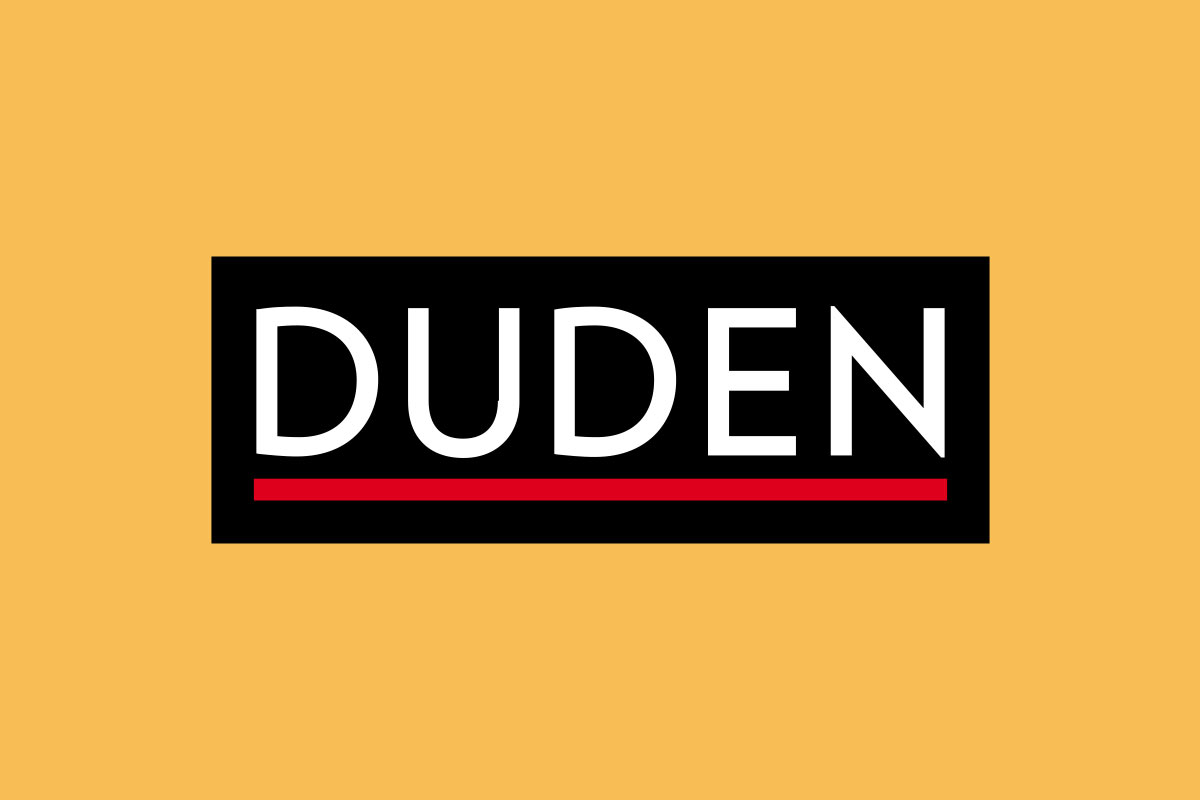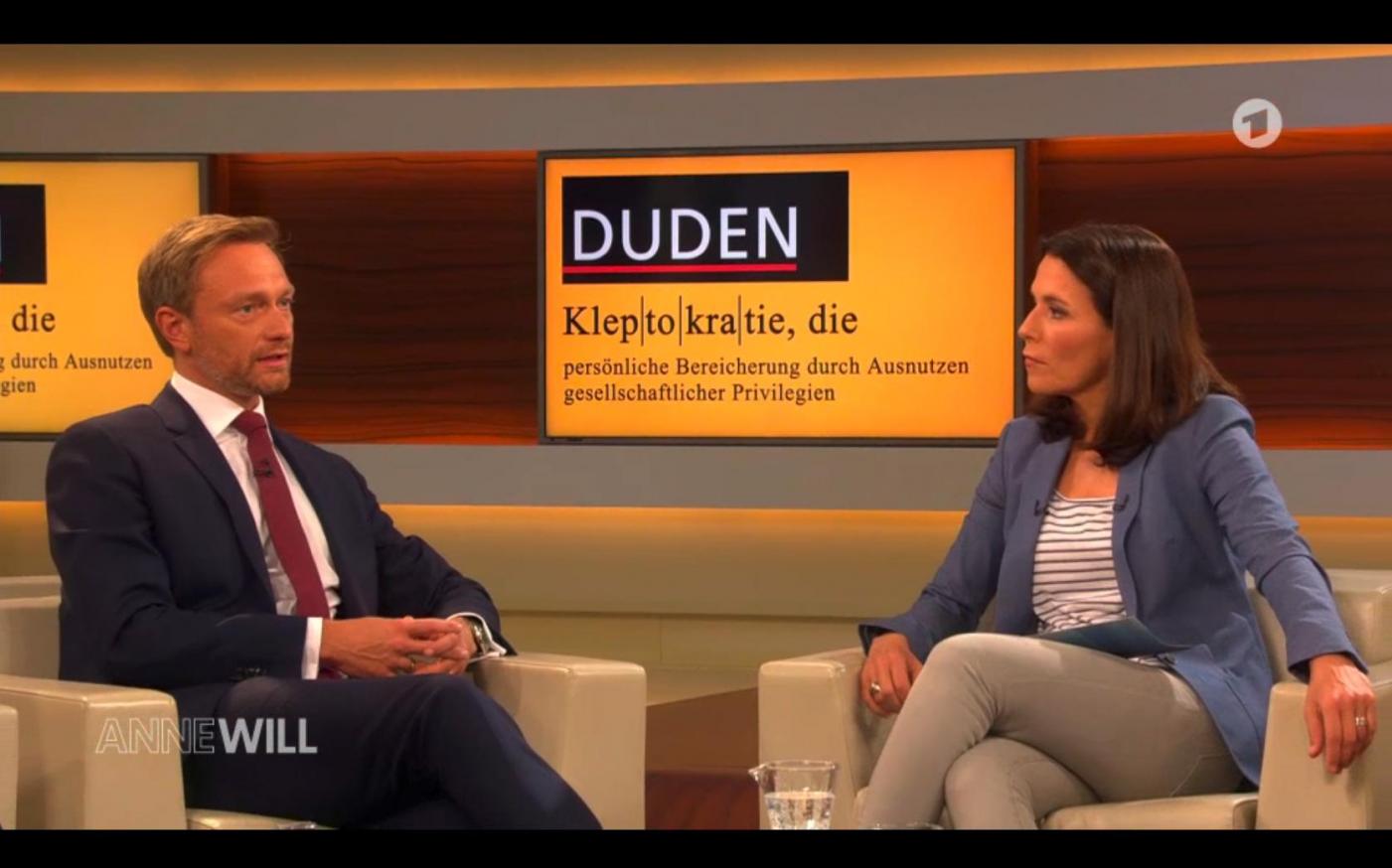
Neues Duden-Design
Vermutlich sollte es »anders, frischer und moderner« aussehen*.
Das aber unter unbedingter Beibehaltung aller signifikanten Gestaltungsmerkmale.
Wasch mich, aber mach mich nicht nass.
Gestalte mich, aber mach mich nicht schön.
*Nachtrag: Das ist die große alte Dame unter den schlechten Briefings.
"Angeschnitten" ist doch schon ein paar Jahre wieder vorbei. Unnötiges Aufbrechen der Ordnung – lässt bei mir Zweifel an der Ernsthaftigkeit aufkommen. Schade. Die sattere Farbe ist ja ein guter Schritt, ich hätte aber eher ein Gelb (so kennen wir den Duden) als ein Orange genommen.
Ich finde, dass es nicht grundsätzlich schlecht ist, Text an- bzw. abzuschneiden. Nur in Bezug auf die neue Ausgabe des Dudens sieht der angeschnittene Schriftzug nach Lückenfüller aus. Einer der beiden Schriftzüge „DUDEN” verkommt zum rein grafischen Element. Der Umgang mit den Leerräumen ist also bei der neunten Auflage besser. In Bezug auf die Funktionalität hätte einer völlig ausgereicht. Darüber hinaus ist der helle Text auf dem Orange nicht gerade gut lesbar.
Aber auch das Design des Covers der neunten Auflage ist nicht wirklich gut. Die versetzte unterstreichende Linie reicht bis zum linken Rand. Vermutlich weil der Text recht nahe am linken Rand der schwarzen Fläche liegt. Die Linie sieht so zwar „definierter” aus, aber im Grunde ist sie ohnehin überflüssig.
Na ja, so richtig mach ich dieses Schriften-Durcheinander da auch nicht. Mindestens 3 verschiedene, und DUDEN in 2 Verschiedenen Schriften?
Frohes Fest – da könnte ich jetzt länger drüber schreiben (und geht dann schon mal gut los), weil ich an dem »Relaunch« des Duden im Jahre 2000 maßgeblich als Freelancer beteiligt war (siehe „Vorher“). Die Reinzeichnung der Logotype (meist angeschnittenes schwarzes Fähnchen, wurde dann aber auch alleinstehend als Logo eingesetzt), stammt von mir, basierte auf einer minimal modifizierten Frutiger Roman.  Vorher gab es kein »Duden-Logo«, es gab zwar eine grafische Linie in der Einbandgestaltung, die auf einer durch Günter Gerhard Lange überarbeiteten Times basierte. Der Gedanke, den Markennamen Duden in eine grafisch konsistente Form zu bringen, sprich also eine Logotype zu gestalten, die als Element der Einbandgestaltung, wie auch alleinstehend Verwendung finden konnte, war damals neu.
Dennoch gab es einige Konstanten, wie z.B. den „Regenbogen“ für die Kernbände, die beibehalten wurden – die Pixel kamen später dazu. Der Spektralverlauf ist eine Erbschaft von Willy Fleckhaus, der das spektakulär bei der edition suhrkamp in die Verlagsbranche eingeführt hat, was auch wunderbar funktioniert, wenn man viele Einzelbände zur Verfügung hat, bei zwölf Bänden wird die Sache ein bisschen schwierig. Nichtsdestotrotz haben wir viel Energie darauf verwendet, den Verlauf zu optimieren bzw. durfte ich diesen Part übernehmen – was dann dazu führte, das die vorher verwendeten Vollton-HKS-Töne einer etwas aufgehellten Farbreihe wichen, was auch der Wahrig in seinem Redesign damals übernommen hat, naja, im Prinzip wurde das ganze grafische Konzept für den Duden, daß wir entwickelt hatten, vom Wahrig abgekupfert.
Die Frutiger kam nebst der Kepler im durch Iris Farnschläder parallel überarbeiteten Innenteil zum Einsatz, auf den sich die Umschlaggestaltung ganz klar bezieht (wir waren während der Arbeit nicht mit ihr im Kontakt, bekamen aber die eingesetzten Fonts durch den Verlag übermittelt und haben auch die Gestaltung gesehen, glaube ich).
Farbigkeit Duden Band 1: der bekannteste Duden und eines der auflagenstärksten Bücher in Deutschland ist natürlich Ausgangspunkt eines jeden Redesigns – also das markante Gelb, wie Bertel schon bemerkte. Zusammen mit dem Schwarz und der roten Linie (diese ist also nicht völlig unnötig, Herr Enslin) in der Logotype addierte sich dies zum Dreiklang analog der bundesdeutschen Staatsflagge. Wir haben diesen ziemlich offensichtlichen Zusammenhang damals nicht ignoriert, es gab aber auch ganz andere Vorschläge innerhalb der Agentur.
Unser Grundgedanke (Agentur: Bender + Büwendt, Berlin) beim Design, das sich zunächst mal auf die Aufgabe bezog, die Umschlaggestaltung der Kernbände 1–12 zu überarbeiten, ging in Richtung Verlagserscheinungsbild. Dies hat sich dann tatsächlich über die Jahre auch so etabliert, z.Zt. verwenden drei Verlage – Duden Verlag, Duden Schulbuch, Fischer Duden – die Logotype als zentrales Gestaltungselement, das grafische Konzept ist also aufgegangen. So, jetzt aber mal die bunten Teller vorbereiten …
Funktioniert doch aber nur bei dem Rechtschreib-Duden. Aber ich gebe zu, dass ich zumindest nicht bewusst wahr genommen habe, dass es sich um die Farben der deutschen Flagge handelt. Kommt davon, wenn man den Stofffetzen ignoriert, wo immer es geht. Jedenfalls spricht das insofern für das Duden-Design, weil ich die Flagge selbst unschön finde, sofern ich sie nicht in Trophäensammlungen wie dieser sehe. Unter ästhetischen Gesichtspunkten finde ich eh nur die alte lybische gelungen. :-) Tja, Gaddafi war schon irgendwie stylish. Deswegen käme übrigens auch nur der Katholizismus  für mich in Frage, sollte ich jemals auf die blöde Idee kommen, religiös zu werden. Frohes Fest übrigens!
Hätte man das angeschnittene DUDEN nicht in einem Grauwert oder Gelbwert anlegen sollen? Ich finde es greift sich den Blick und der eigentliche Titel des Buches geht unter; zumal DUDEN ja redundant erscheint‽